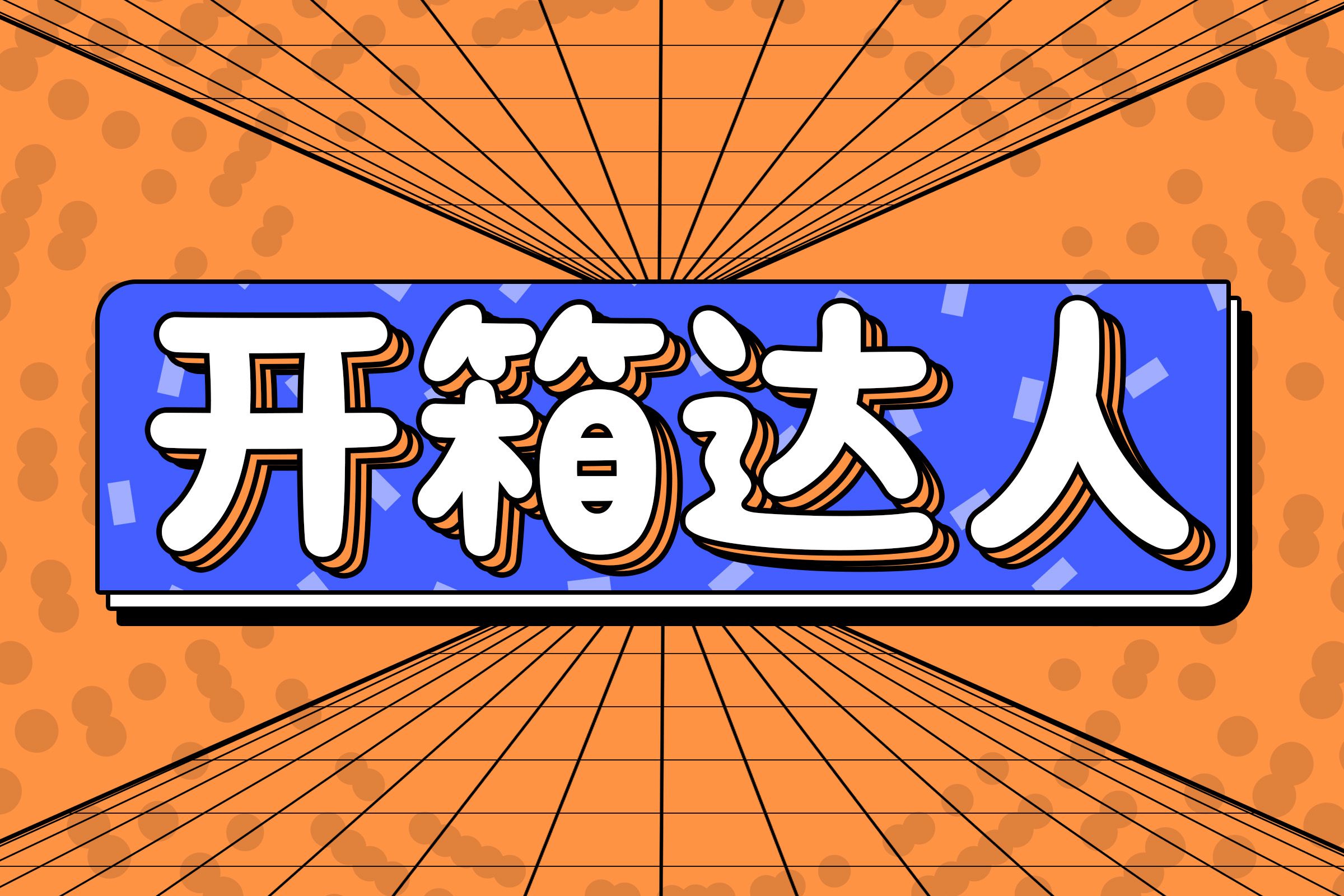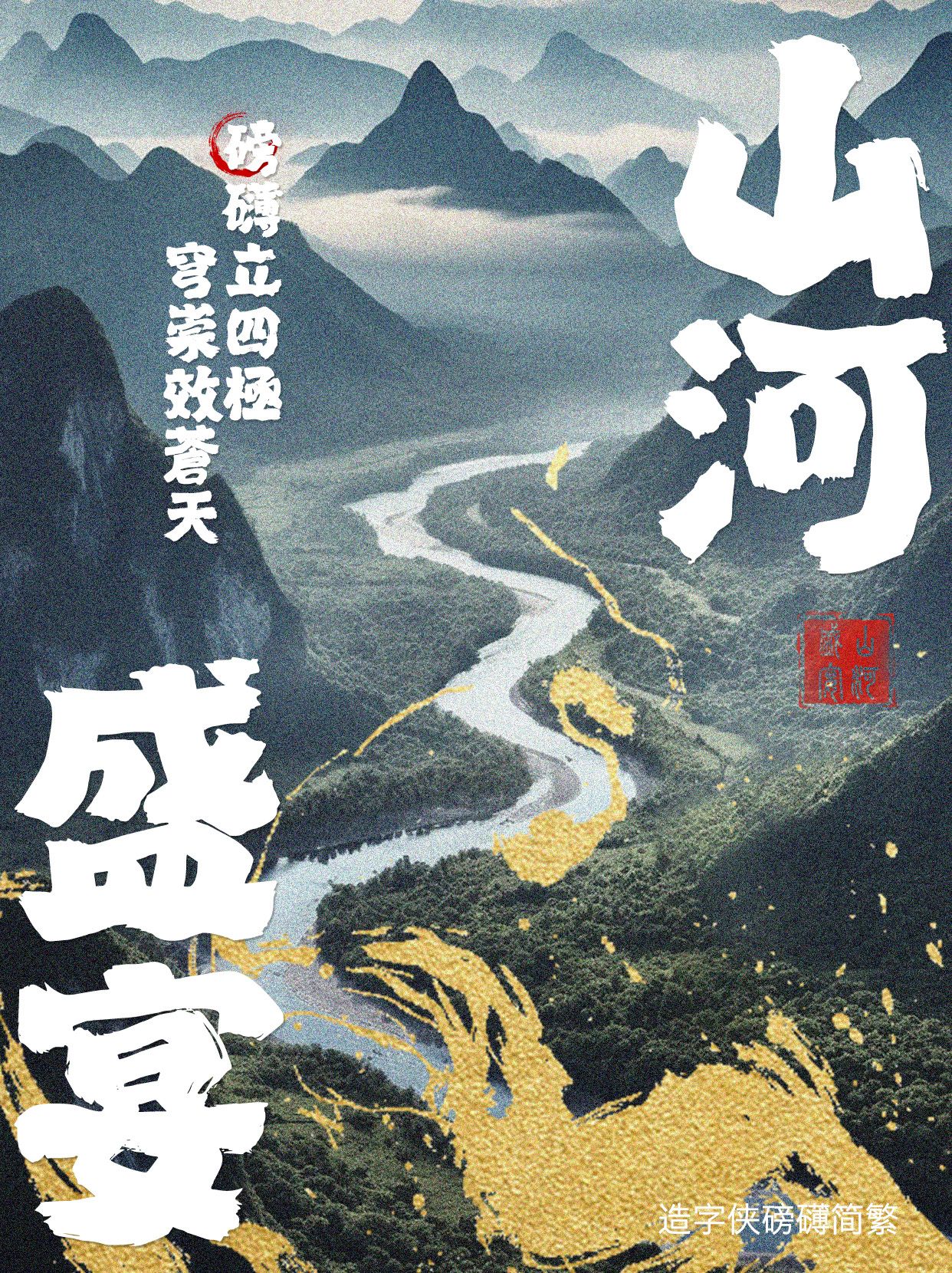
字跃屏上,型动视界!四款媒体场景字体赋能视觉表达新可能
媒体时代的视觉革命,始于对文字个性的精准捕捉。以下四款字体以突破性设计语言,为不同媒介场景提供风格化解决方案:
一、造字侠郝刚快乐简 微黑
当112°倾斜角遇上隶书蚕头燕尾,这款字体在矛盾中达成惊艳平衡。西文斜体的浪漫基因注入汉字骨架,使标题设计既保持文化厚度,又焕发摩登气息。其韵律感特别适合时尚杂志专题页、文化类短视频封面,在斜而不倒的动态平衡中,传递"优雅破界"的视觉宣言。
二、造字侠磅礴简繁
笔画飞白与方圆转折构成视觉交响,这款字体的情绪张力堪比电影运镜。粗细分明的线条自带聚光灯效应,在新闻专题报道中可强化事件冲击力,于综艺海报设计则能传递狂欢氛围。其"一波三折"的运笔节奏,恰似镜头语言的蒙太奇切换,让平面文字产生叙事动感。
三、励字山中精灵简
拙朴线条勾勒的童趣世界,这款字体是二次元文化的视觉代言。均匀布白与惊喜细节并存的设计,既满足儿童节目包装的亲和力需求,又能为手游界面注入奇幻色彩。其"稚拙美学"恰如数字时代的童话滤镜,让Z世代受众瞬间捕获治愈感。
四、喵字字幕体
专为新媒体打造的这款字库,深谙屏幕阅读的底层逻辑。开放字形突破传统字框限制,年轻化元素在保持易读性的同时,为视频弹幕、社交媒体九宫格注入鲜活气息。其"数字原生"特质,使字体既能承载严肃内容,又适配轻松表达,真正实现多场景自由切换。
从文化杂糅的破界之美,到情绪饱满的视觉交响;从治愈系童真到屏幕原生美学,四款字体构建出媒体用字的完整光谱。建议根据内容调性灵活选用:用斜体字体传递文化碰撞,以飞白笔触强化戏剧张力,让童稚线条唤醒情感共鸣,借开放字形对话年轻群体。当文字成为媒介革命的先锋,每一次排版都是视觉叙事的再创造。